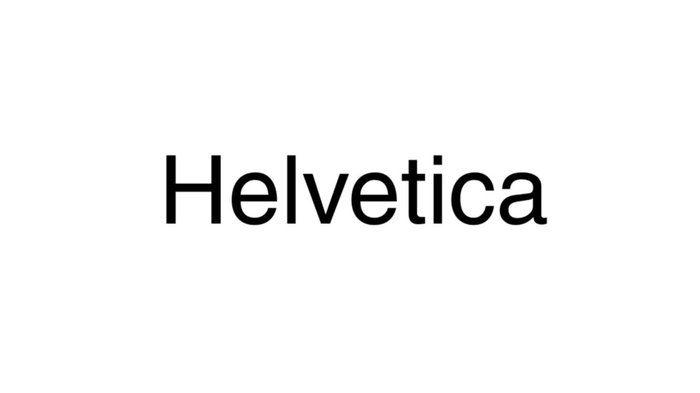
Font yang Sering Digunakan untuk Logo. Logo, adalah salah satu bagian penting yang harus dapat Anda rumuskan pertama kali saat menjalankan bisnis. Logo adalah bagian penting dari proses business planning. Adanya logo akan mempermudah pebisnis untuk memperkenalkan brand value dan juga brand identity nya kepada target audience.
Lalu, bagaimana kriteria logo yang baik?. Jika Anda sudah membaca artikel MinTiv sebelumnya tentang 7 Contoh Logo Simple dan juga Artinya, Anda pastinya sudah tahu bahwa logo yang baik terdiri dari 5 kriteria penting. 5 kriteria itu adalah;
5 kriteria ini, dapat Anda jadikan sebagai acuan utama ketika ingin membuat sebuah logo. Adapun jenis logo yang dapat Anda kreasikan sendiri beragam. 2 yang paling populer adalah logo model monogram dan juga logo model wordmark.
Logo model monogram adalah logo yang memanfaatkan 2,3,4 huruf sesuai dengan nama brand yang dicanangkan. Sedangkan logo model wordmark, hampir mirip dengan logo model monogram, hanya saja seluruh huruf dari nama brand dicantumkan.
Dari penjelasan di atas, kita dapat mengetahui dengan pasti bahwa font menjadi bagian penting untuk kedua jenis logo tersebut. Apabila Anda ingin membuat logo bisnisnya dengan model monogram atau wordmark, Anda harus memikirkan font yang terbaik.
Nah, di dalam artikel ini, MinTiv akan menjelaskan tentang 7 jenis font yang sering digunakan untuk logo, cocok untuk Anda jadikan sebagai referensi. Penasaran apa saja?, simak baik-baik artikel ini ya!.
Jenis font yang sering digunakan untuk logo pertama, adalah font Helvetica. Font ini termasuk ke dalam jenis keluarga Sans Serif. Sering digunakan untuk keperluan dokumen online seperti dalam desain website atau konten artikel online. Helvetica memiliki kesan yang klasik dan juga minimalis. Ada banyak perusahaan besar yang menggunakan font ini dalam logo mereka. Salah satu contohnya adalah Panasonic.
Jenis font yang sering digunakan untuk logo kedua adalah Didot. Font jenis ini memiliki ciri khas yang begitu kentara. Anda dapat mengetahuinya dari kontras yang tinggi, serta perpaduan garis tebal dan tipis yang menciptakan kesan dimensi begitu kuat. Karakteristik yang dimiliki Didot ini, menjadikannya cocok diterapkan untuk bisnis yang mengedepankan nilai elegan klasik. Salah satu contoh perusahaan yang menggunakan font ini adalah Giorgio Armani.
Berikutnya, adalah font Trajan. Font ini terinspirasi banyak dari huruf romawi kuno. Tidak heran jika font ini memiliki nilai klasik bersejarah yang tinggi. Aura elegan yang dimiliki oleh Trajan tidak perlu diragukan lagi. Tidak heran juga jika Trajan sering digunakan sebagai font penamaan judul film klasik Romawi. Ada banyak brand terkenal yang menggunakan Trajan ini untuk logo mereka, salah satunya adalah Victoria’s Secret.
Selanjutnya ada Mountain. Sesuai dengan namanya, font ini menggambarkan dimensi penulisan huruf naik turun, atau bergelombang. Penulisannya yang seperti ini, menjadikan font Mountain memiliki kesan minimalis dan abstrak yang kuat. Meskipun bergelombang, font ini masih bisa dibaca dengan baik dari berbagai sudut, jarak dan juga layar yang berbeda.
Jenis font yang sering digunakan untuk logo selanjutnya adalah Baltica. Font jenis ini menawarkan penggunanya sentuhan modern yang begitu kental. Garis-garis tambahan yang keluar dari setiap huruf, menandakan bahwa daya kreativitas yang dimiliki Baltica, tidak terbatas.
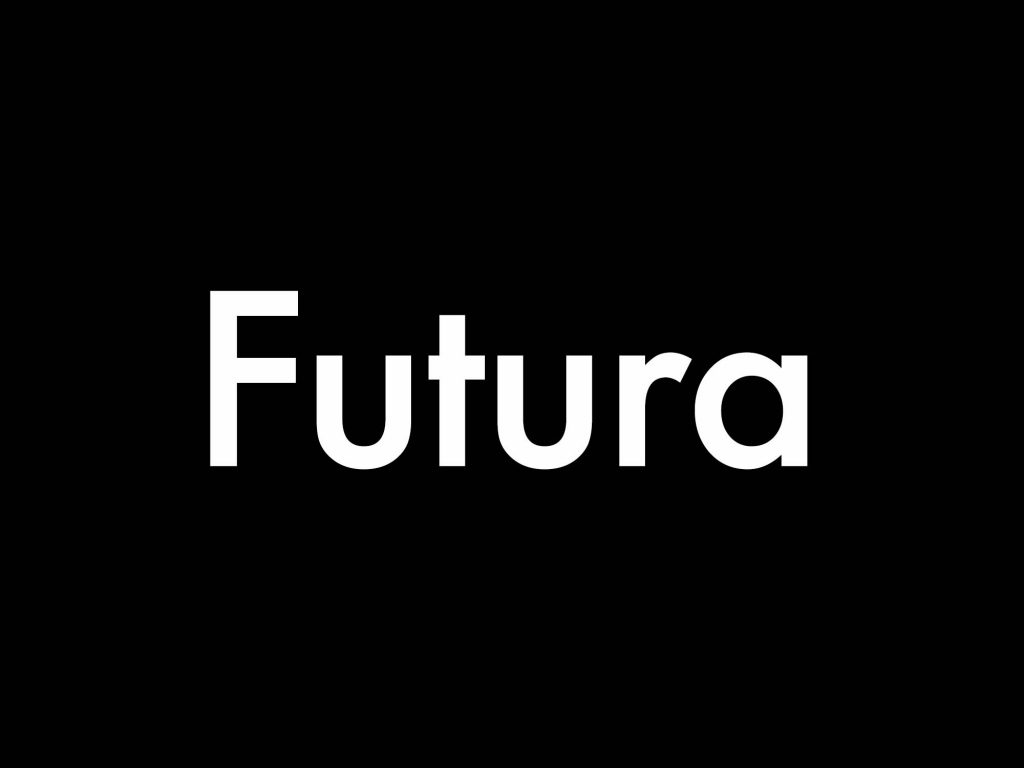
Menjelang akhir, ada Futura. Futura adalah font yang memiliki kesan sederhana, bersih dan juga modern yang begitu kental. Font ini hadir dengan gaya ringan tetapi tebal, miring dan juga kental. Diketahui bahwa Futura adalah bagian dari keluarga font nan yakni Akzidenz-Grotesk. Ada banyak brand ternama yang menggunakan jenis font ini ke dalam logo mereka. Salah satunya adalah Calvin Klein.
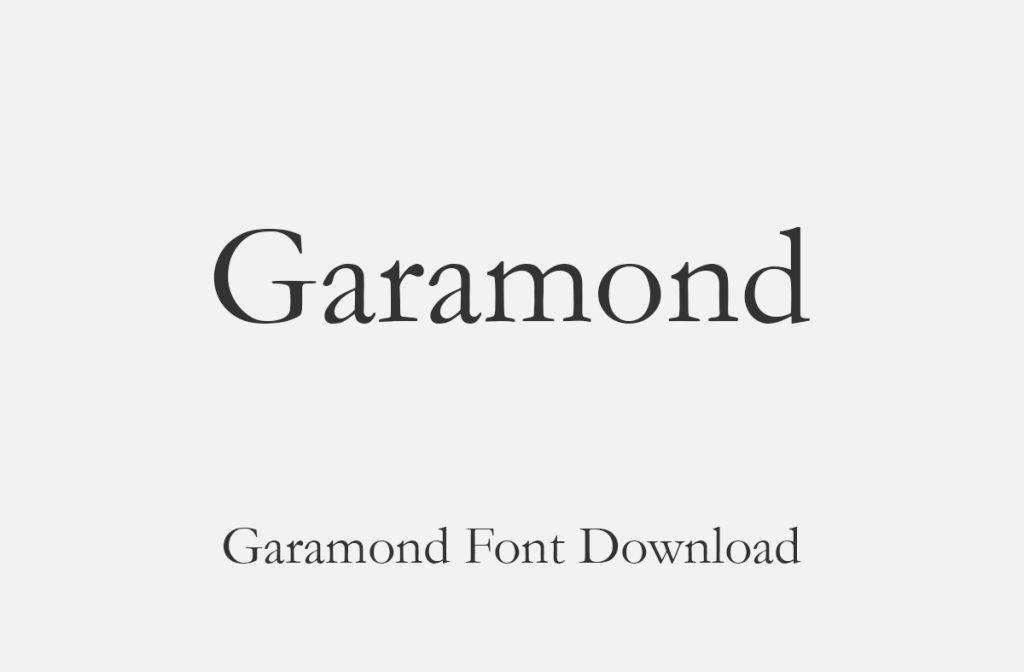
Jenis font yang sering digunakan dalam logo terakhir adalah Garamond. Jenis font ini, termasuk ke dalam jenis tipografi serif lama. Garamond memiliki tingkat keterbacaan yang sangat baik. Selain itu, Garamond punya dimensi elegan yang begitu kental. Biasa digunakan untuk majalah, website, dan juga buku.